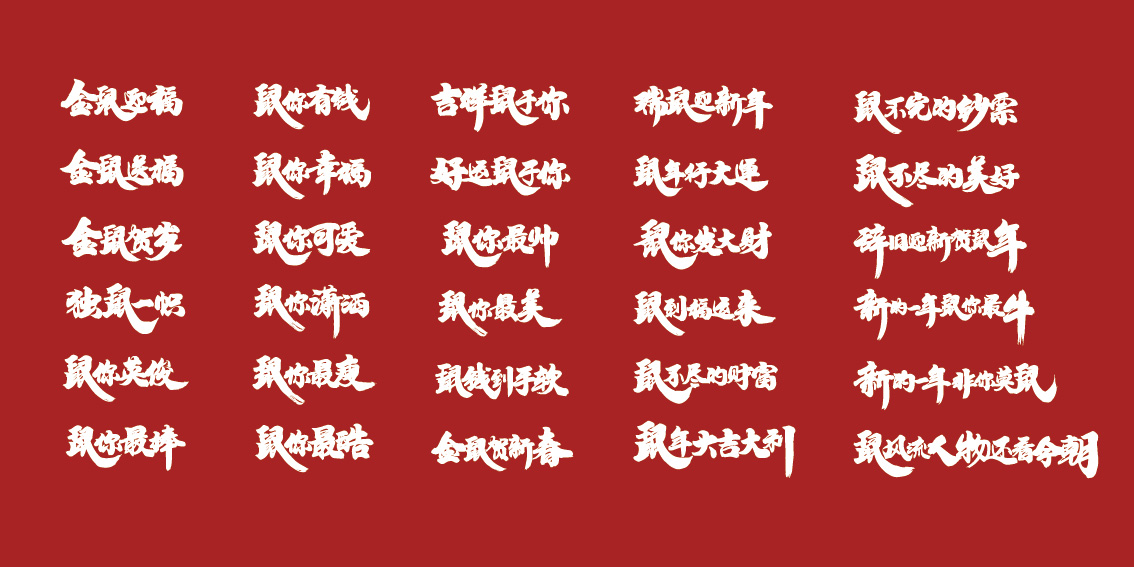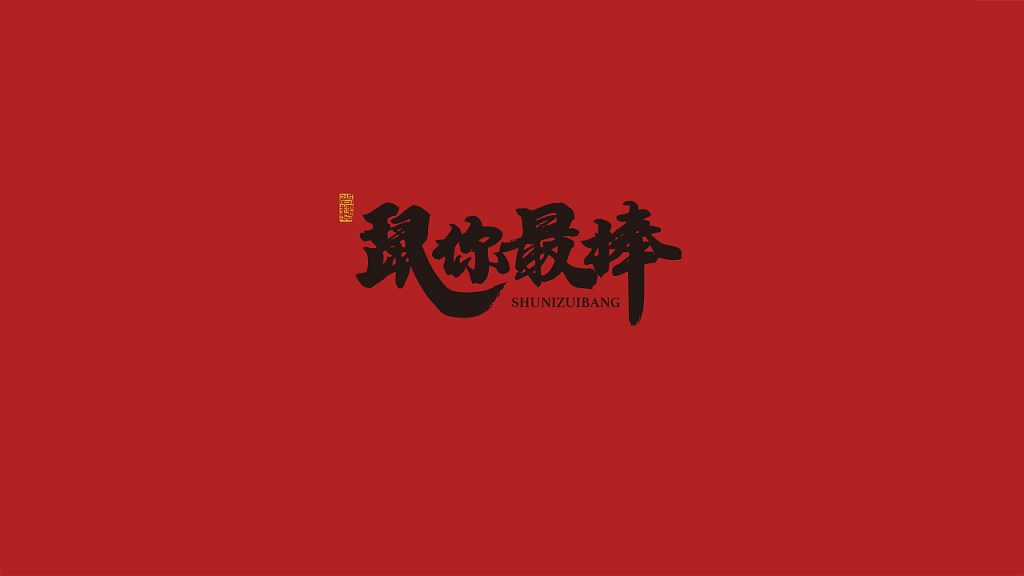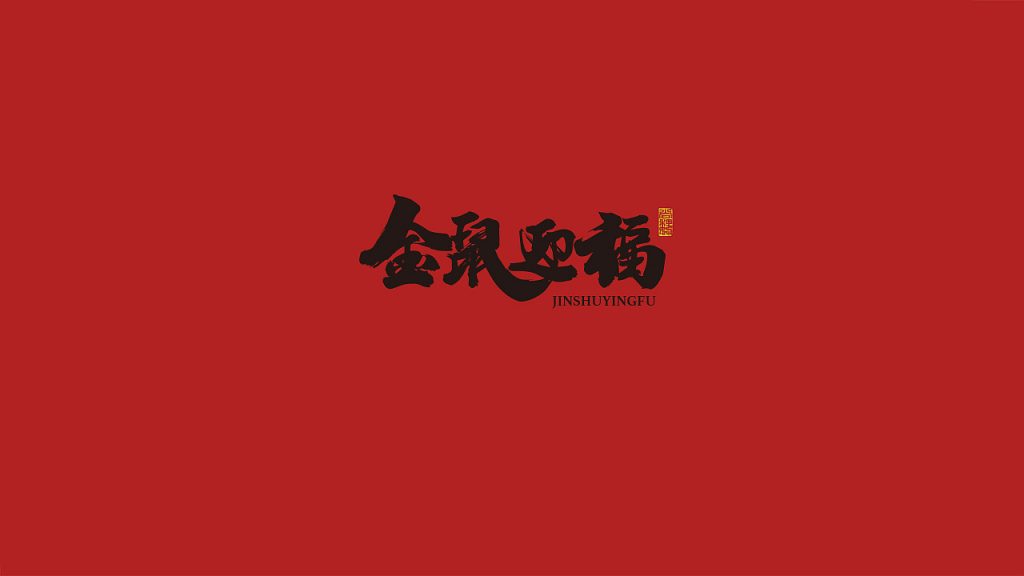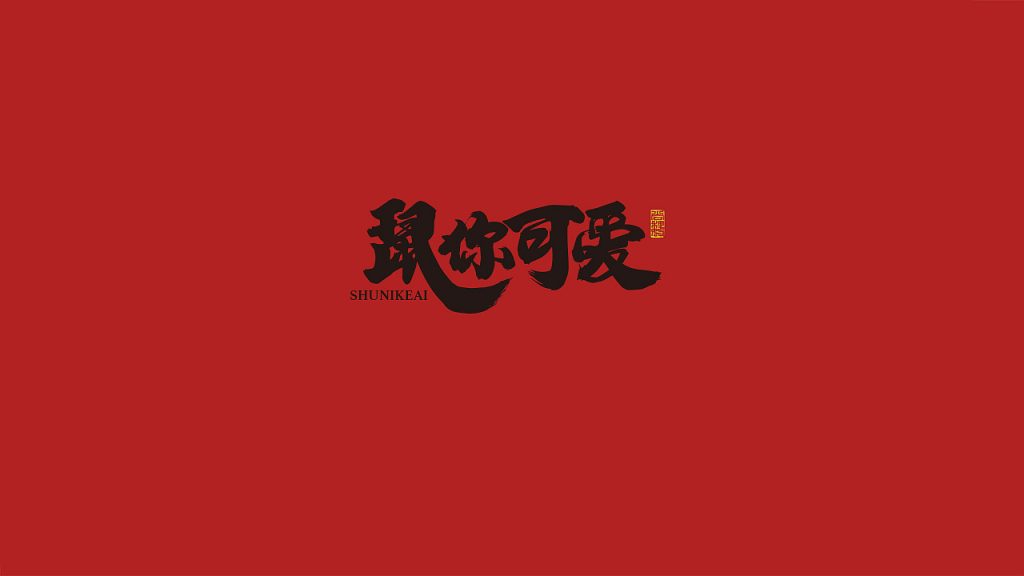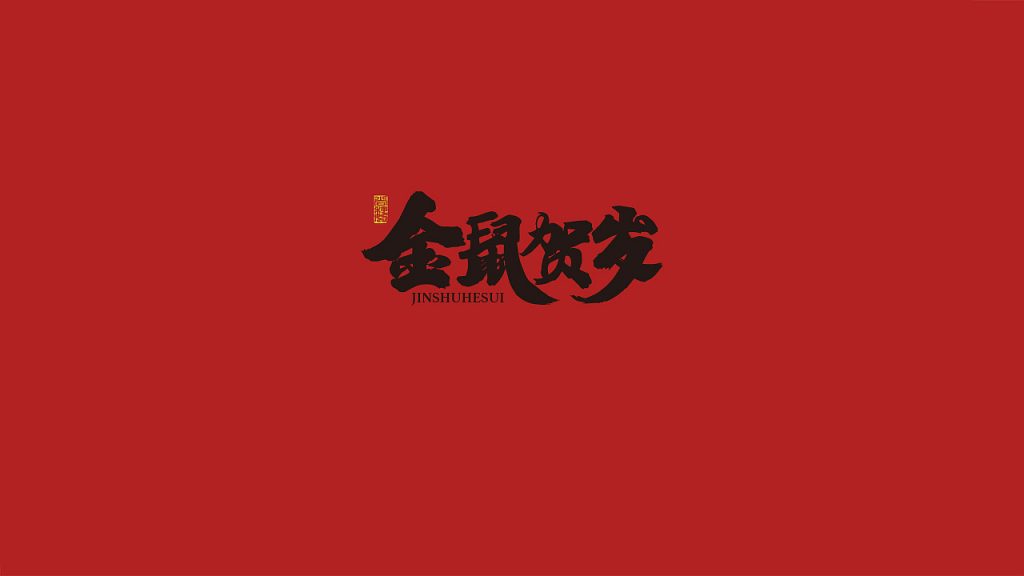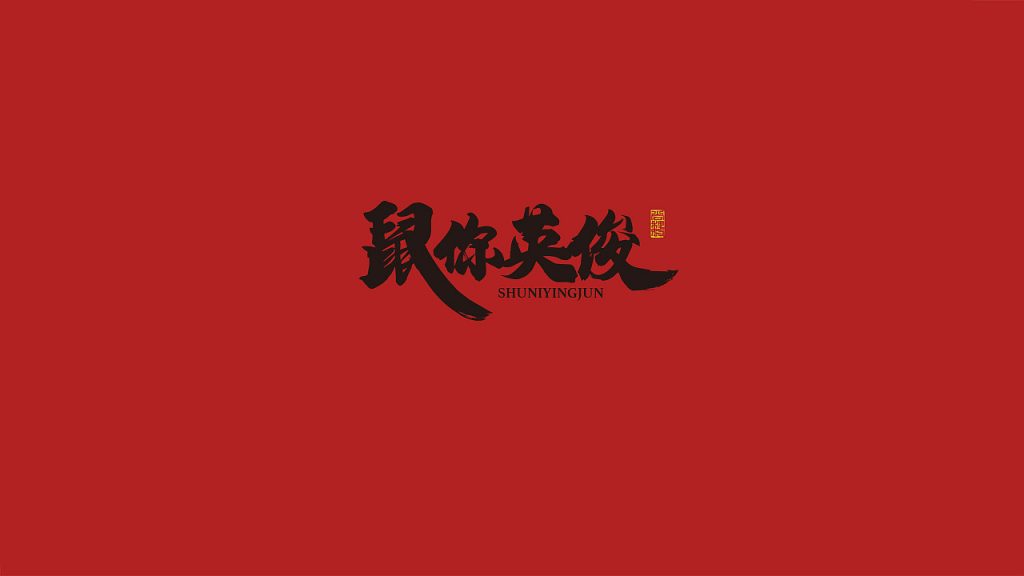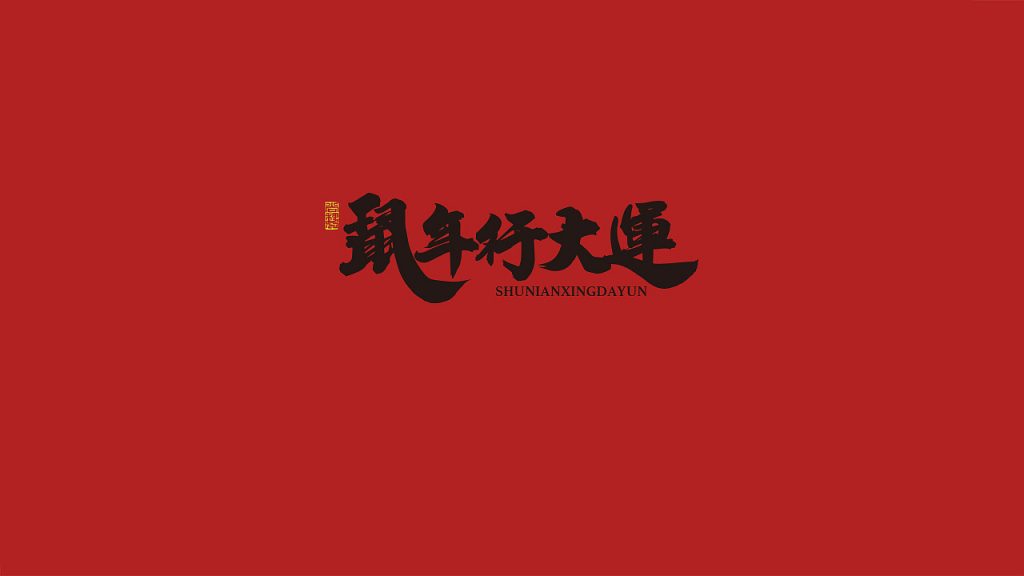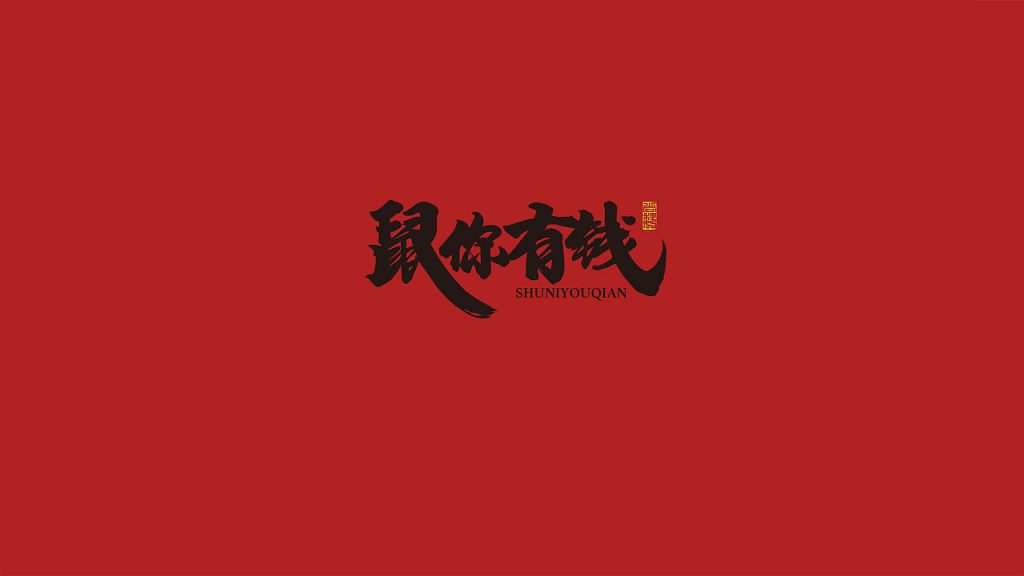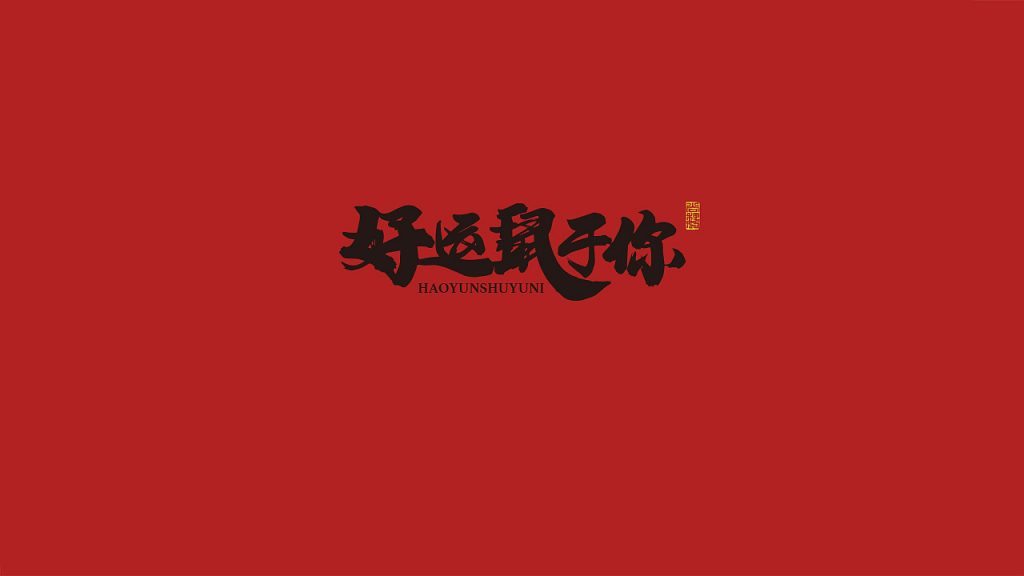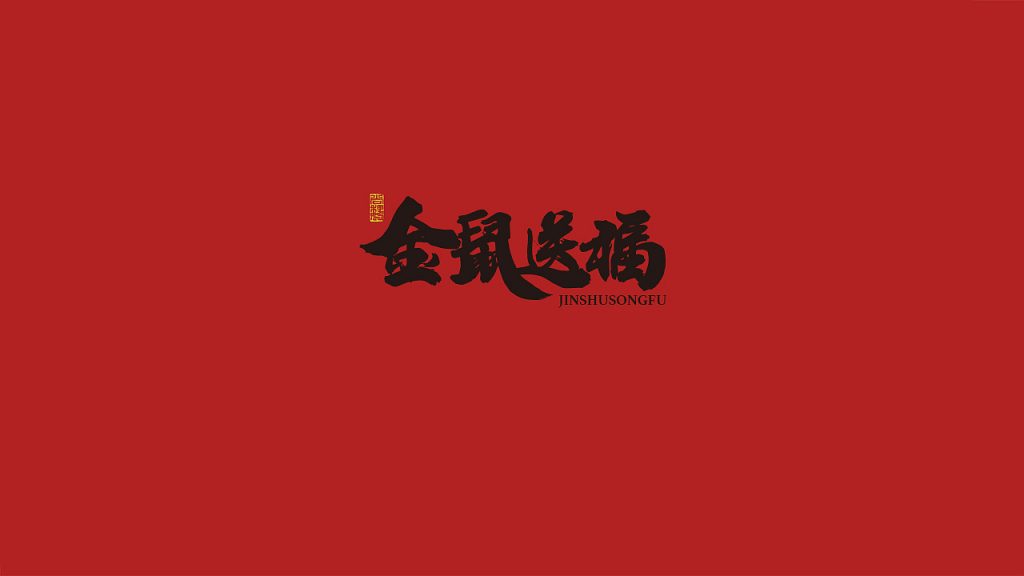
尚巍大神发布,30款鼠年祝福语手写字体免费商用
说起手写字体界的大神级人物“尚巍”,或者设计新手或小白可能没有听过他的名字,但说起《我不是药神》这个电影,估计大家应该都会有所印象吧。不错,《我不是药神》的字体设计正是大佬“尚巍”的杰作。尚巍是站酷人气设计师,著有著作《字不语》。
这次尚巍大神特地为我等设计界小白送上福利,新的一年,为大家写了一组鼠年祝福语。可免费商用、任意、无限制使用。这套活动字体笔锋流畅,苍劲有力,特别适合做活动专题,海报等的标题字体。最重要的是,大神不但为你把祝福语想好了,还写好了送给你。用上这些标题字体,就感觉跟《我不是药神》同一档次了,简直就是到达了设计人生的巅峰,哇哈哈哈……如果老板质疑你的字体不够大气,你可以怼回去说这是设计大神专门为我们公司定制的字体,不要给脸不要脸啊!这波操作6666……